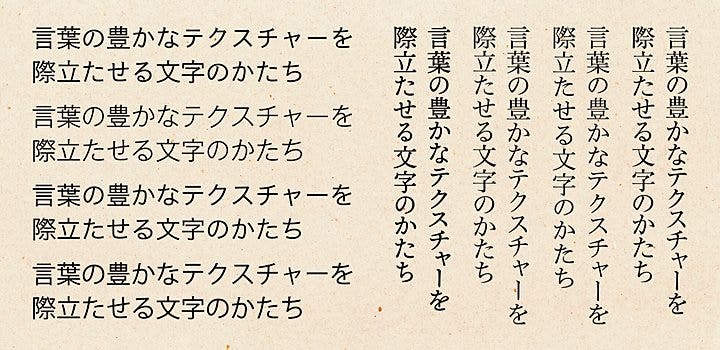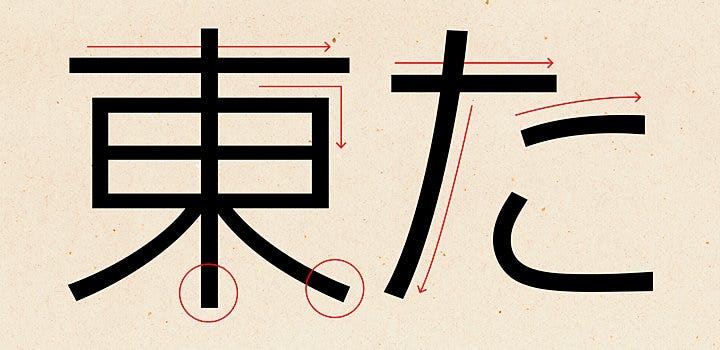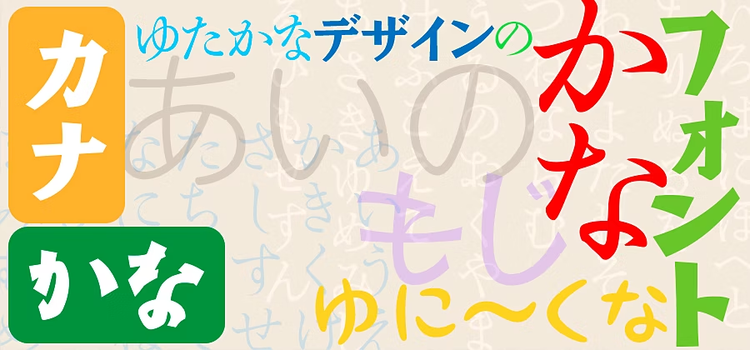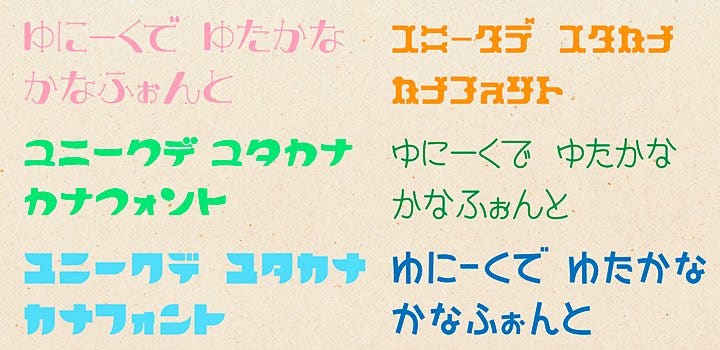
日本語のかなのデザインとフォント
日本語の表情を豊にし、特徴づけているのは、ひらがなやカタカナといった日本独自の文字を漢字と組み合せて使用している点にあります。ひらがなだけやカタカナだけでも日本語として読むことはできますが、漢字かな交じり文として表現されこそ、日本語らしさが際だちます。ここではあらためて、かなフォントやカタカナフォントの特徴と魅力を見てみましょう。
デザインの印象を左右する「かな」
日本語の表記は漢字にひらがなやカタカナを交えることで成立するもので、ひらがなやカタカナは平安時代のころから漢字をもとにして発展し作られてきました。
一方、漢字は中国で時代とともに使われる書風も変遷し発展していき、それぞれが歴史を重ねていったうえで近代の活字が成立する過程で漢字に調和するかな書体が確立していきました。現在使われている日本語フォントは、明朝体とゴシック体がおもに使われるほか、草書体や楷書体のように筆で書いたかたちを再現したものなどが用いられますが、フォントを特徴づけ印象を左右しているのは「かな」のデザインによるところが強くあります。その理由は日本語の文章において、漢字よりもかなの割合の方が多いこと、漢字に比べてかなはそのかたちに変化をつけやすいことが挙げられます。
また、かなは漢字の一部から作られたり、漢字をくずして書くところから成立してきた経緯があり、フォントのデザインでも筆で書いたときの動きやつながりは引き継がれています。この動きやつながりは漢字よりも色濃くデザインに反映される傾向が強いため、かなの微妙なデザイン差があるだけでもフォントの印象が異なって感じられることになります。
明朝体とかな
明朝体は中国の明王朝時代に広く用いられた書体が活字となり、現在のフォントのデザインへとつながっていますが、その特徴は横線が細く縦線が太いメリハリのある点と、横線の右端に「ウロコ」と呼ばれる三角形の山が強調されたデザインになっている点があvります。
ただしこれは漢字だけにある特徴で、明朝体とされるフォントのかなには横線と縦線の太さに差はなく、ウロコもありません。フォントとしての明朝体に使われているかなは何かというと、実は楷書体なのです。これは漢字が成立して変遷してきた歴史と、かなが成立して変遷してきた歴史が異なるためです。
明朝体のフォントには、昔の活字を再現してデザインされたものから、現代になって新しくデザインが作られたものまで、さまざまな種類があり、古典的な明朝体は「ふところ」といわれる線と線で構成される内側の空間が比較的狭く、近代的な明朝体ではこの空間が広めになっている傾向があります。
それぞれのかなも、漢字と調和するようにこの空間が調整されていたり、古典的なものでは筆のつながりがより強調されたデザインになっている傾向があります。
ゴシック体とかな
ゴシック体は縦線と横線が基本的に同じ太さで、明朝体の特徴となっているウロコを持っていないデザインが特徴です。これは漢字でもかなでも同じで、明朝体のように漢字は明朝体で、かなは楷書体ということはなく、漢字であってもかなであっても同じゴシック体であるといえます。ゴシック体のデザインが日本で用いられるようになったのが近代になってからで、新たに設計されたため漢字もかなも筆書きの特徴を持たず同じようにデザインされたと考えることができます。
なお、ゴシック体も古典的なものは、ふところが狭くデザインされていて、近代的なものではふところが広めに作られているという傾向は明朝体と同じで、もちろん、かなも同じようにデザインされて漢字との調和がとられています。また、近代的なゴシック体は横線も縦線も水平垂直で構成され、より幾何学的なデザインになっているのも特徴です。ゴシック体には角に丸みを持たせた丸ゴシック体もあり、丸ゴシック体のかなも、もちろん角は丸みを帯びて、漢字と同じイメージになるようにデザインされています。
かなフォントとアプリケーションでの使い方(Adobe Illustrator)
日本語のフォントは漢字、ひらがな、カタカナ、アルファベットがすべて用意されているものがほとんどですが、かなだけで構成されたフォントも作られています。
しかし、かなフォントだけで日本語を表現するのは不可能なので、漢字のフォントと組み合わせて使う必要があります。フォントはテキストを選択して文字パネルからフォントを指定すれば変更することはできますが、かなだけを選んでその都度、フォントを変更するのは効率的ではありません。
Illustratorでは「書式」メニューの「合成フォント」から、漢字、かな、全角約物、全角記号、半角欧文、半角数字にそれぞれフォントを割り当てて、文字の種類ごとに異なるフォントを割り当てたものを1つのフォントとして扱うことが可能です。
この合成フォントとして保存したものは、文字パネルから1つのフォントのように指定することができるようになり、合成フォントの内容を変更して上書き保存すると、適用しているフォントも一括で変更内容が反映されます。また、合成フォントは文字の種類ごとにフォントを変更するだけではなく、サイズも個別に変えることもできるので、デザインを細かく調整することも可能です。
かなフォントとアプリケーションでの使い方(Adobe InDesign)
合成フォント機能はIllustratorだけではなく、InDesignにも搭載されていて、同じようにフォントの組み合わせを作ってテキストに適用することができます。
合成フォントの機能では漢字、かな、全角約物というように文字の種類を区別するので、ひらがなであってもカタカナであっても、かなとして1つのフォントしか指定することができませんが、InDesignではひらがな、カタカナ、アルファベットにそれぞれ異なるフォントを指定した文字スタイルを用意しておいて、段落スタイルの正規表現スタイルから文字の種類に合わせて文字スタイルを適用する正規表現を設定しておくことで、Illustratorではできない細かなフォントの変更を行うことが可能になります。
正規表現スタイルを設定した段落スタイルは、テキストを入力するごとに、文字の種類に応じてフォントが変更されていきます。正規表現スタイルでは、特定の文字列ごとに決まったかなフォントを指定するということも可能なので、「アドビ」と「アドビフォント」という文字でフォントを変えるといった場合でも対応することができます。
一世を風靡したカタカナフォント
最後に少し特殊なカタカナフォントを紹介しましょう。
今でもこそ、日本語の文章にはカタカナが多く使われていますが、ひらがなに比べて割合は少なく、日本語の文章における表情を決めるという点では、ひらがなよりも影響が少ないということもあります。
しかし、1990年代後半、デジタルに強いデザイナーたちによって、さまざまなカタカナフォントをリリースされました。これは、当時のフォント作成ツールの日本語対応状況が限られていたということも関係しています。
フォントを作成するツールは、いま、極めて高機能で操作性にもすぐれた「Glyphs」というアプリケーションがスタンダードとなっていますが、それ以前はフォントメーカー以外でユーザーがフォントを作成できる環境は、Fontographerというアプリケーション以外にあまり選択肢がありませんでした。
Fontographerはもともと欧文フォントを作成するためのもので、事実上、日本語のフォントを作成することはできませんでした。しかし、A〜Z、a〜zの文字と発音記号付き文字などの領域を利用してカタカナを割り当てることは可能だったので、1バイトカナフォントといわれるフォントを作成するブームが巻き起こったのです。この時期には個性的なデザインの1バイトカナフォントが数多く配布されました。
日本語の文字をすべて作成しようとすると2万字以上が必要になりますが、当時のFontographerにはそのような領域がなく、また、インターネットの回線も今より低速だったため、容量の大きな日本語フォントをダウンロードするのも現実的でありません。しかし、1バイトカナフォントであれば容量は小さく、作成する字数もカタカナと記号類などで済むというのもブームとなった背景でした。